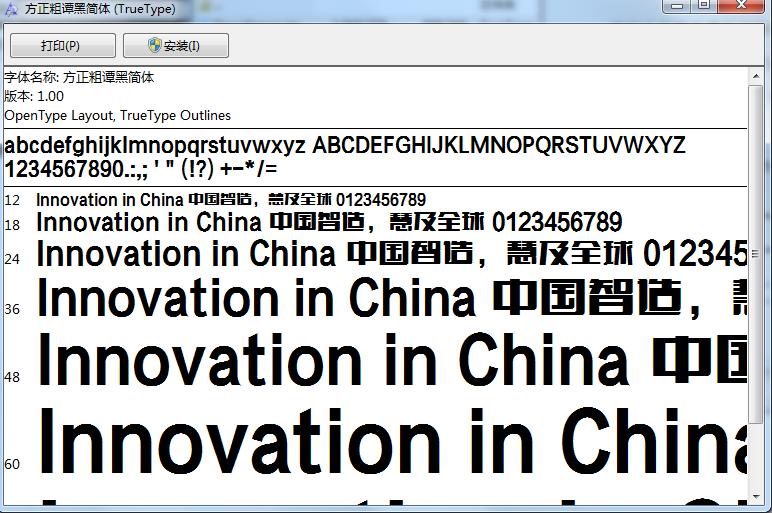
fzcthjw gb10字體的別名又叫方正粗譚黑簡(jiǎn)體,這款字體使用非常廣泛,字形寬扁,線(xiàn)條比較粗,看起來(lái)非常霸氣,喜歡的朋友歡迎來(lái)綠色資源網(wǎng)下載哦!
方正粗譚黑簡(jiǎn)體下載,本字體包括符號(hào)及英文和數(shù)字共9000多個(gè)字,耗時(shí)2年一筆一劃十分苛刻和精心完成。因?yàn)槌踔允怯闷放圃O(shè)計(jì)中的中文字體設(shè)計(jì),在單字和細(xì)節(jié)雕琢過(guò)多,不能兼顧整體,所以本字體不宜很多字成排使用。